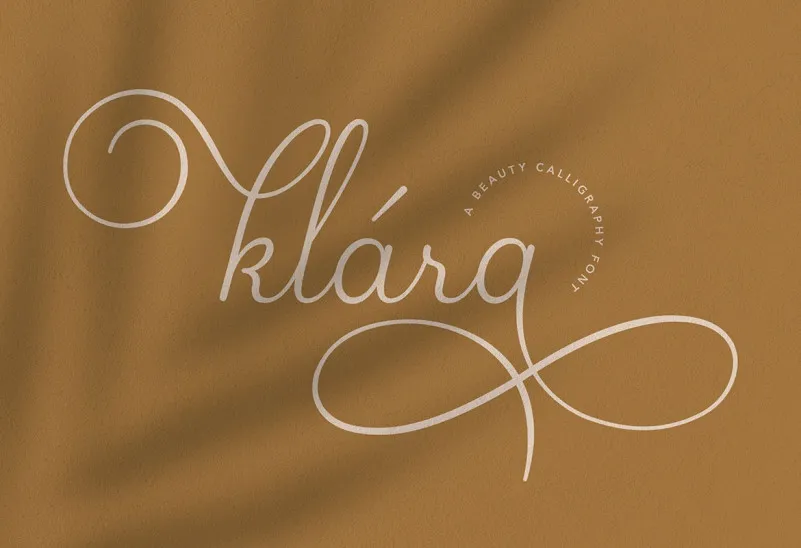
A Klara Font é uma elegante tipografia à base de cólums criada para atender aos designers que buscam um toque único e sofisticado em seus projetos. Com estilo moderno, ela oferece uma aparência harmônica e envolvente que vai ao encontro dos mais variados ambientes digitais ou impressos. Destinada a aqueles que valorizam elegância e bom gosto, essa fonte é perfeita para trabalhos como convites de casamento, citações, frases motivacionais e criação de marcas femininos. Também se adequa à criação de logotipos elegantes, revistas para mulheres, websites e qualquer outro projeto que precise de um toque autêntico e refinado. Com Klara Font na sua coleção, você garantirá um design único e sofisticado em todas as obras que criar.